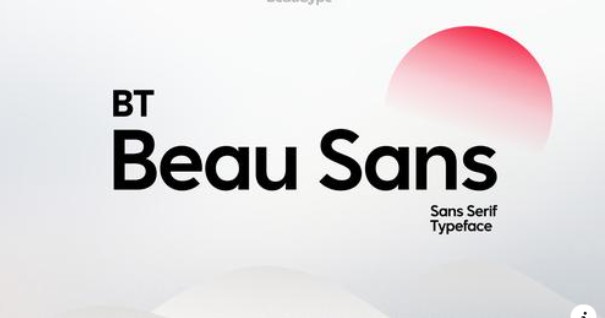
Giới thiệu về Font Tiếng Việt BT Beau Sans Typeface
Trong cộng đồng thiết kế đồ họa tại Việt Nam, việc tìm kiếm một bộ Font Chữ vừa hiện đại vừa hỗ trợ đầy đủ bảng mã tiếng Việt luôn là ưu tiên hàng đầu. Font Tiếng Việt BT Beau Sans Typeface chính là giải pháp hoàn hảo mang lại sự cân bằng giữa tính thẩm mỹ và công năng sử dụng. Đây là một bộ phông chữ thuộc phong cách sans-serif (không chân) với những đường nét thanh mảnh, dứt khoát nhưng không kém phần mềm mại, giúp các bản thiết kế trở nên chuyên nghiệp và tinh tế hơn bao giờ hết.
Tại sao nên chọn Font Tiếng Việt BT Beau Sans Typeface?
Đặc điểm nổi bật của bộ font này chính là sự đa dạng trong các biến thể từ cực mảnh (Thin) đến cực dày (Bold). Điều này cho phép người dùng linh hoạt ứng dụng vào nhiều loại hình tác phẩm khác nhau. Đặc biệt, phiên bản việt hóa của Font Tiếng Việt BT Beau Sans Typeface đã được tối ưu hóa các dấu câu tiếng Việt, đảm bảo không bị lỗi hiển thị khi soạn thảo trên các phần mềm thiết kế như Photoshop, Illustrator hay các ứng dụng văn phòng cơ bản.
Ứng dụng thực tế và cách cài đặt hiệu quả
Sử dụng trong giáo dục và sáng tạo
Văn phong của bộ chữ này rất phù hợp với môi trường học đường, giúp các bài thuyết trình hay tài liệu học tập trở nên dễ đọc và thu hút hơn. Font Tiếng Việt BT Beau Sans Typeface thường được dùng để thiết kế bìa sách, làm infographic hoặc tạo các tiêu đề nổi bật trên trang web. Với cấu trúc hình học hiện đại, nó giúp truyền tải thông điệp một cách rõ ràng, trực quan nhất đến người xem.
Kết luận về bộ font chữ việt hóa ấn tượng